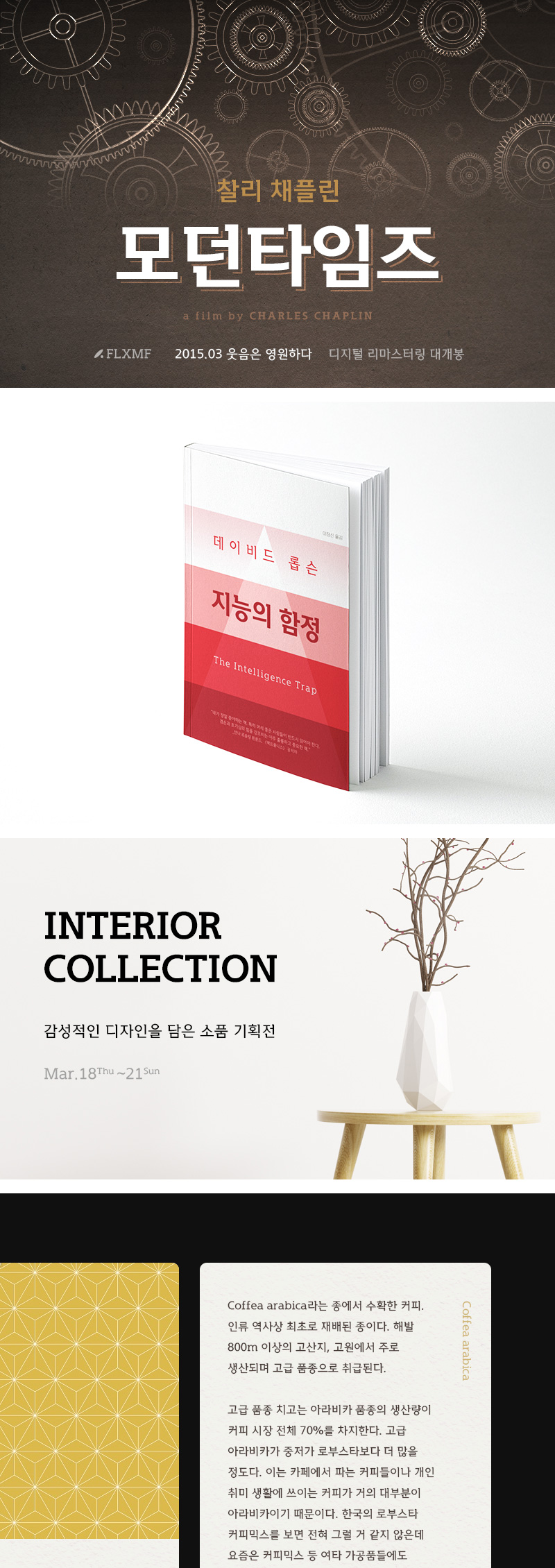
Rix모던타임즈는 굵은 직사각 형태의 슬랩 세리프와 유연한 곡선 획의 조화가 특징인 서체입니다.
사용성을 높인 3종의 웨이트로 획의 두께에 따라 다양한 느낌을 연출할 수 있습니다.
특유의 단정하고 간결한 형태가 북 커버, 포스터 등 각종 인쇄물의 텍스트나 영상의 자막으로 활용하기 좋습니다.